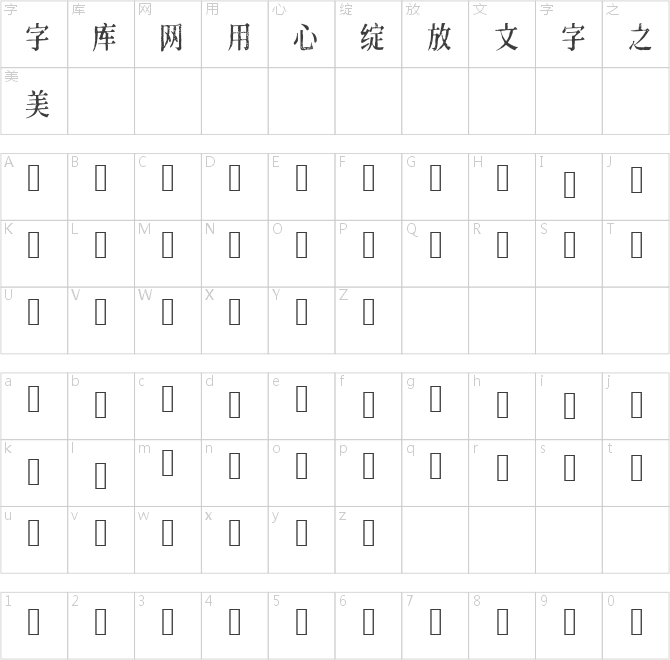
字体名称: 令东齐伋体
令东齐伋体
• 修正了0.0.1版中的以下的字错误
• 字|宇、
令东齐伋体字体黄令东齐伋体QIJIFALLBACK字库是一款让人赏心悦目、百看不厌的中文字体,适合各类广告和产品包装设计应用,字体大小37.03MB,格式为ttf字体,上传用户是迷路的猪,作者/版权方为黄令东